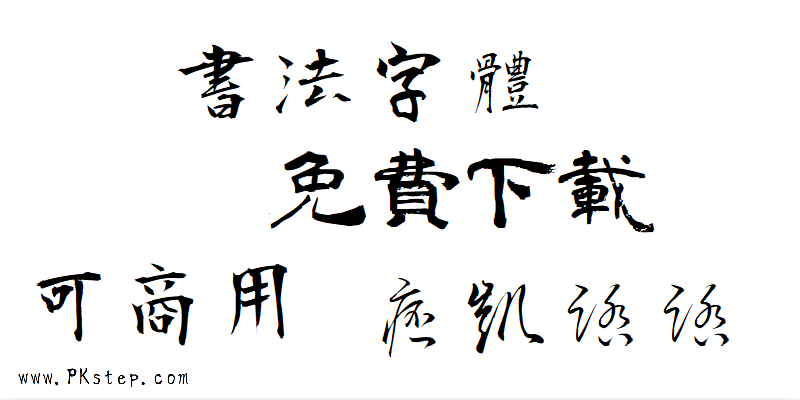
免費書法字體下載!由日本網站武藏推出的具有中國風的毛筆字體,共6款可免費下載,包含青柳、橫山毛筆、草書、行書、隸書等…雖然是日本的字體,但繁體中文也能套用,部分可能會有缺字,但是還是超級棒的免費字體資源,趕緊手刀下載把這些字型收藏起來吧~可供個人與商用,不用擔心版權問題。
第1款:書法字體下載-青柳稀疏石字體。
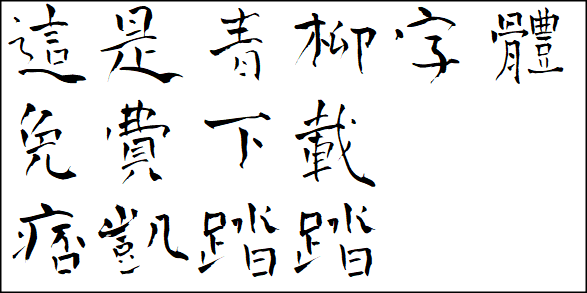
第2款:書法字體下載-衡山毛筆字體。
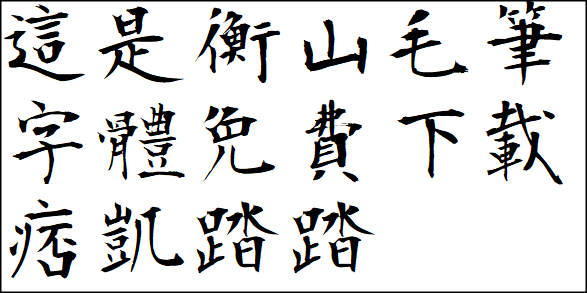
第3款:書法字體下載-青柳衡山字體。
第4款:書法字體下載-衡山毛筆フォント行書。
第5款:書法字體下載-衡山毛筆フォント草書。
第6款:書法字體下載-青柳隷書。
第7款:莫大毛筆字體。
第8款:莫大毛筆字體。